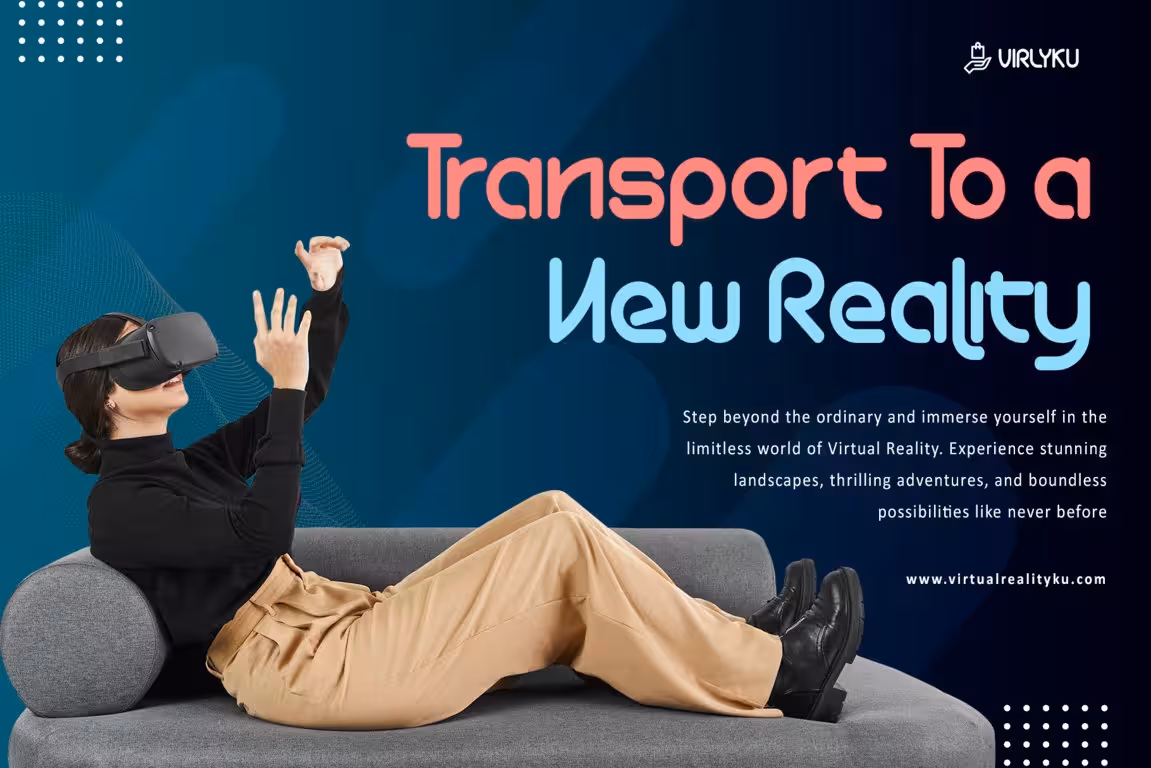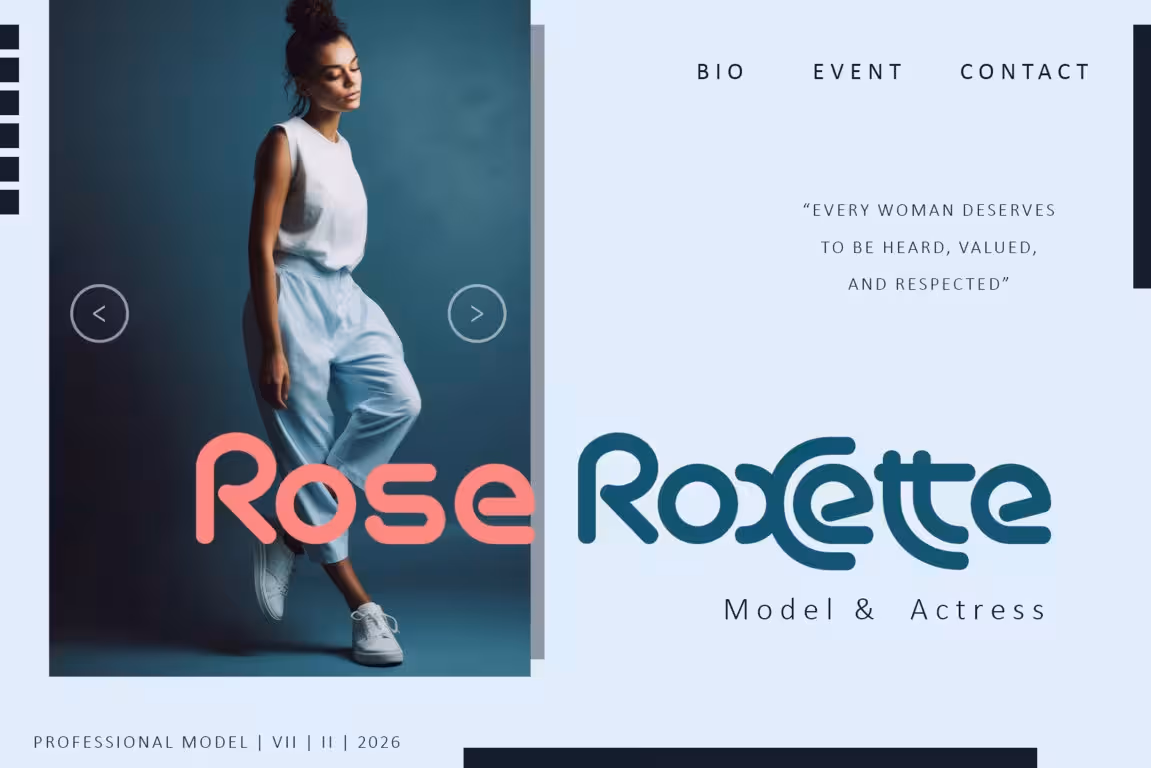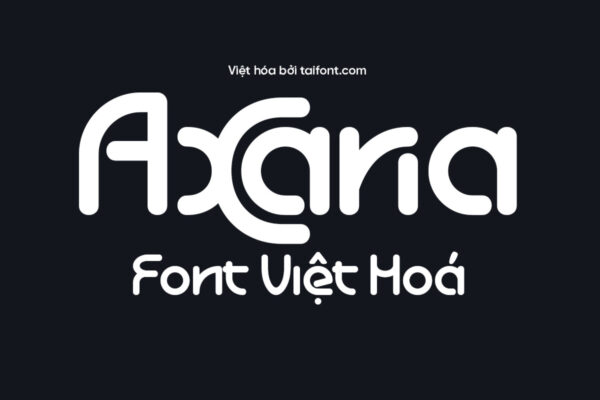
Giới thiệu về Font TF Axaria Việt hóa
TF Axaria Việt hóa là một font chữ không chân (sans-serif) nổi bật với thiết kế hiện đại, năng động và đầy cá tính. Font này có nét chữ bo tròn nhẹ nhàng, tạo cảm giác mềm mại và thân thiện, nhưng điểm đặc biệt nhất là khả năng tùy biến linh hoạt với nhiều ký tự thay thế (alternates). Điều này giúp font không chỉ đa dạng về mặt thị giác mà còn cực kỳ phù hợp cho các thiết kế liên quan đến công nghệ và tương lai.
Với đặc điểm thiết kế độc đáo, góc cạnh bo tròn và khả năng tùy biến cao, Axaria là lựa chọn hoàn hảo cho các ấn phẩm trong lĩnh vực công nghệ, khoa học viễn tưởng và văn hóa đại chúng:
- Thiết kế về công nghệ: Hoàn hảo để sử dụng cho logo công ty công nghệ, giao diện ứng dụng, poster phim khoa học viễn tưởng, hoặc các tài liệu quảng bá liên quan đến AI, robot, blockchain. Font này giúp truyền tải sự tiên phong, đổi mới và sự tinh xảo trong từng sản phẩm, dịch vụ.
- Thiết kế game và truyền thông: Lý tưởng cho logo game, tiêu đề, hoặc các yếu tố giao diện người dùng (UI) trong game có chủ đề cyberpunk, không gian, hoặc các trò chơi tương lai. Nét chữ độc đáo và khả năng tùy biến của font sẽ làm tăng tính chân thực và độ “ngầu” cho trò chơi.
- Thiết kế nhận diện thương hiệu: Có thể dùng cho logo hoặc bộ nhận diện thương hiệu của các công ty, doanh nghiệp muốn truyền tải sự hiện đại, uy tín và sự thanh lịch. Axaria giúp xây dựng một hình ảnh thương hiệu vững chắc và dễ nhận diện.
- Thiết kế poster và banner: Tuyệt vời để tạo các tiêu đề chính (headline), slogan, hoặc thông điệp quảng cáo trên poster, banner, hoặc bất kỳ ấn phẩm nào cần sự chú ý tối đa.
Với TF Axaria Việt hóa, bạn có thể dễ dàng thổi hồn công nghệ, sự độc đáo và cá tính vào các thiết kế, tạo ra những sản phẩm không chỉ đẹp mắt mà còn cực kỳ ấn tượng và có khả năng thu hút sự chú ý tối đa.